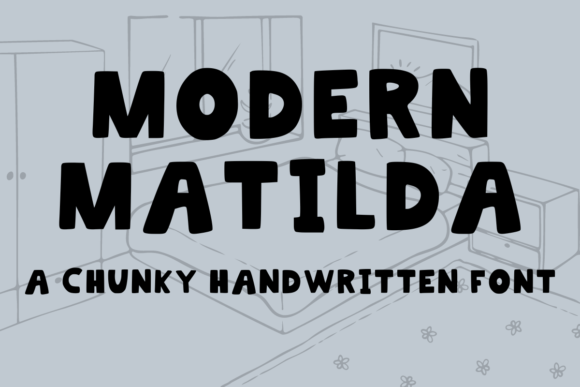
Modern Matilda
Việc tìm kiếm các thành phần thiết kế phù hợp có thể là một thách thức, nhưng Modern Matilda cung cấp một bộ sưu tập đặc biệt giúp nâng tầm công việc của bạn ngay lập tức.
Được chế tác với độ chính xác cao, Modern Matilda cung cấp các vector sạch, kiểu chữ mượt mà và giấy phép thương mại để bạn yên tâm.